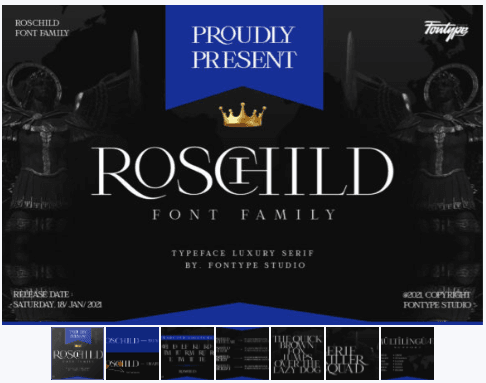
Roschild Font
Roschild - это напористый и подлинный шрифт с засечками. Он великолепно смотрится на свадебных приглашениях, открытках с благодарностями, цитатах, поздравительных открытках, логотипах, визитных карточках и любом другом дизайне, требующем рукописного ввода.